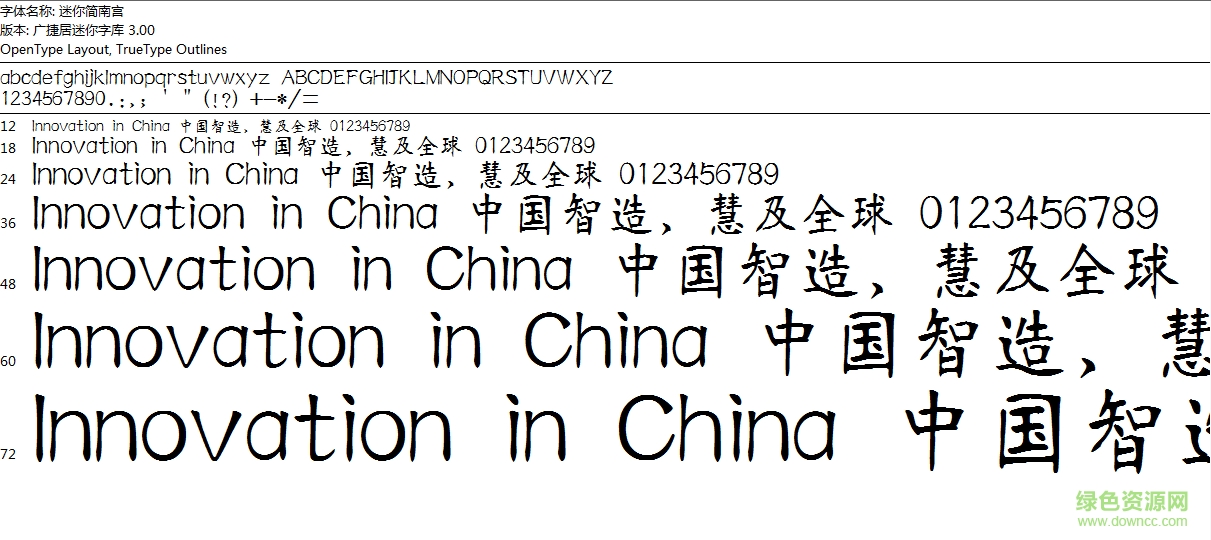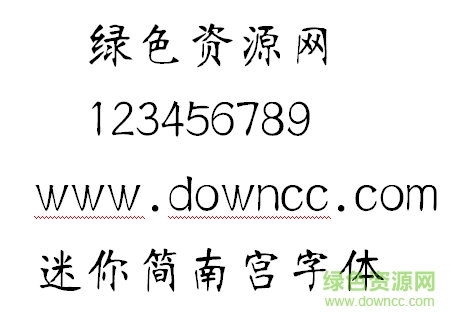
迷你簡南宮是一款適用于鋼筆書法設(shè)計(jì)方面的簡體字體,這款字形大方得體,筆畫分明,每個(gè)字就像刀刻出來一樣,非常好看,喜歡的朋友歡迎來綠色資源網(wǎng)下載體驗(yàn)!
迷你簡南宮字體這款字體筆鋒流暢、美觀大方,整個(gè)字體像鋼筆書寫一樣,非常有手寫特色。此款字體適用于鋼筆設(shè)計(jì),書法設(shè)計(jì)等方面